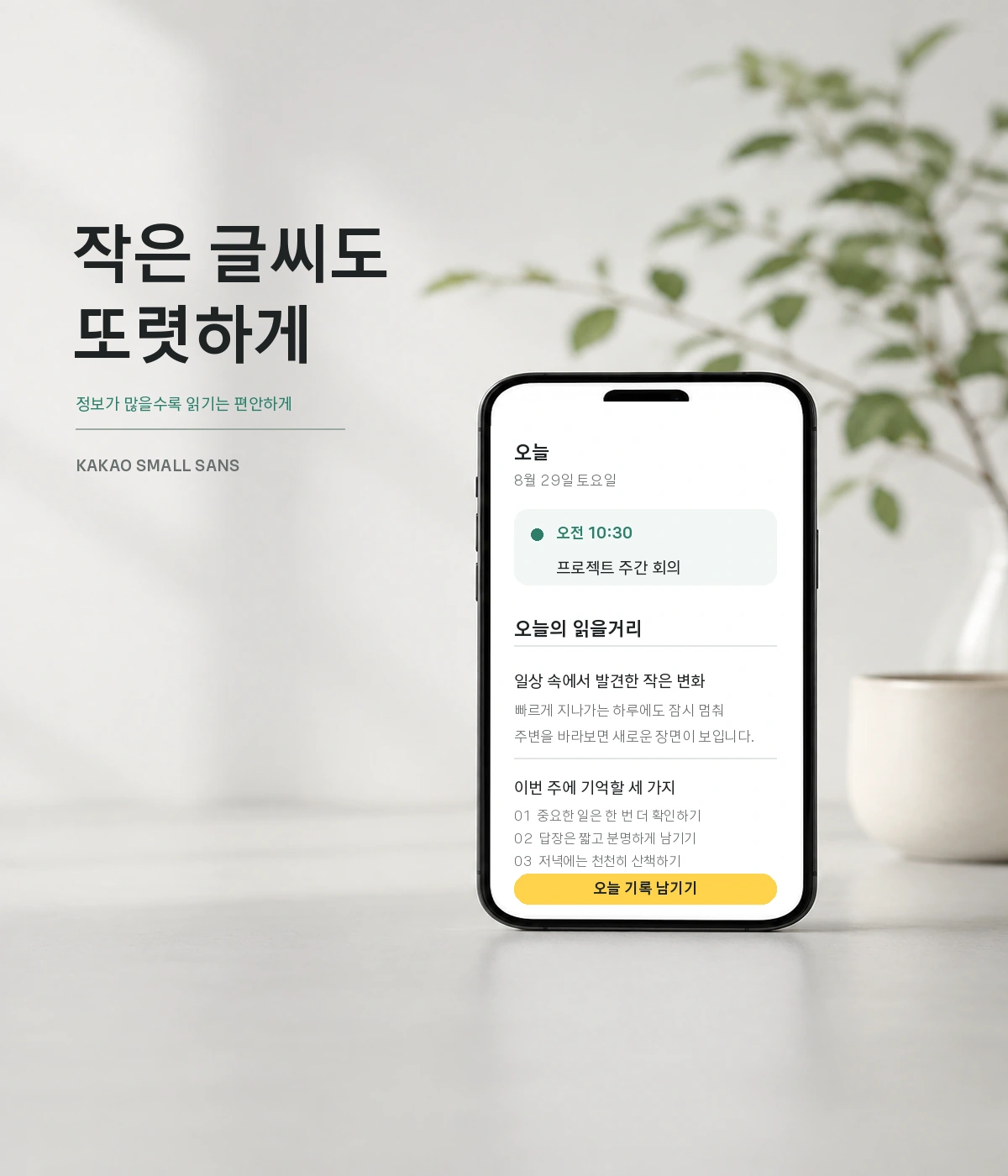
카카오작은글씨 — 카카오에서 배포하는 무료 폰트입니다. 작은 크기에서도 뭉개지지 않도록 글자 사이를 넓히고 선을 정돈한, 화면 본문용 고딕체
카카오가 2025년 6월에 카카오 글씨라는 이름으로 큰글씨와 함께 공개한 두 서체 가운데 작은 쪽입니다. 폰트릭스가 제작했고 개발에 약 2년이 걸렸습니다.
이름대로 작은 크기를 겨냥했습니다. 제작사 설명에 따르면 작은 크기에서도 잘 보이도록 글자 사이 간격을 넓히고 선을 정돈해 뭉개짐 없이 선명하게 보이도록 설계했습니다. 영문 소개는 여기에 속공간을 넓혔다는 점을 덧붙입니다.
요즘의 한국어 소통 방식을 반영한 기능이 둘 있습니다. 하나는 초성입니다. 초성 하나만으로도 뜻이 전달되도록 크기를 키우고 비례를 조정해, 초성을 글자의 일부가 아니라 독립된 글자처럼 쓸 수 있게 했습니다. 다른 하나는 합자입니다. 특정 기호를 입력하면 정돈된 이모티콘 형태로 자동으로 바뀌어, 글자이면서 표정처럼 보이게 했습니다. 굵기는 Light와 Regular, Bold 세 가지이고 오픈 폰트 라이선스로 배포됩니다.